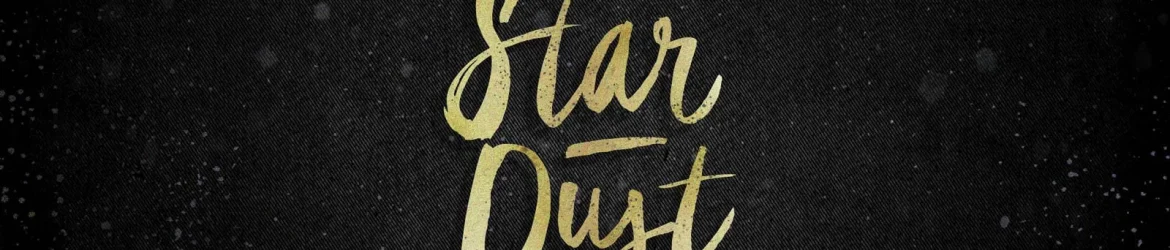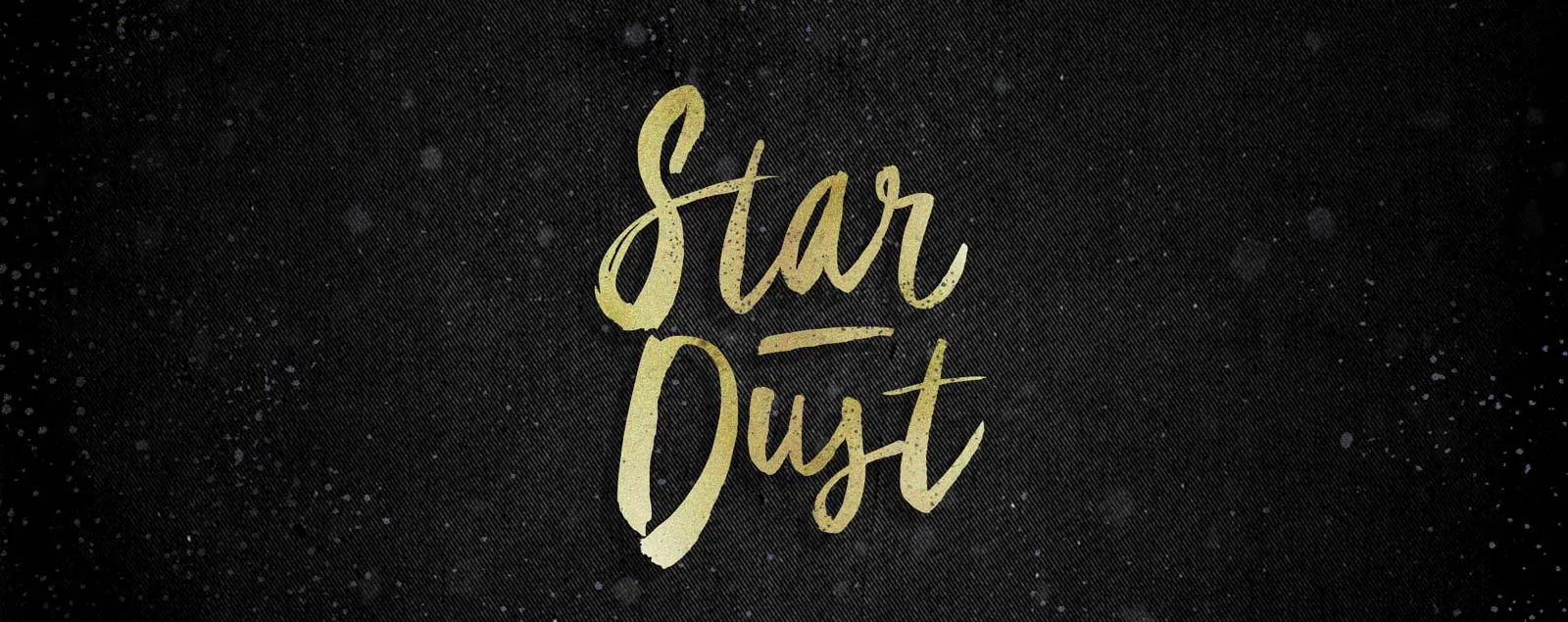
Star Dust Brush Font – Fonte Grátis
Star Dust Brush Font
Star Dust Brush Font é uma elegante e versátil fonte script que traz a sensação de brincar com letras ao seu trabalho. Desenvolvida por blkbktyp, esta fonte retrata um estilo retro tipo typewriter, mas com um toque mais colorido e enriquecido pelo uso da técnica do pincel. As linhas suaves são decoradas com detalhes delicados e uma camada de graça, criando um aspecto que remete ao desenho a mão de um artesão. Ideal para criações de logotipos, identidades visuais, designs web, convites, cartões de visita e qualquer tipo de produto personalizado, Star Dust Brush Font oferece uma linguagem única e divertida capaz de tornar seus trabalhos ainda mais atraentes. Seja você um designer ou um profissional de marketing, certamente encontrará aqui uma fonte que complementa perfeitamente sua paleta de recursos gráficos.